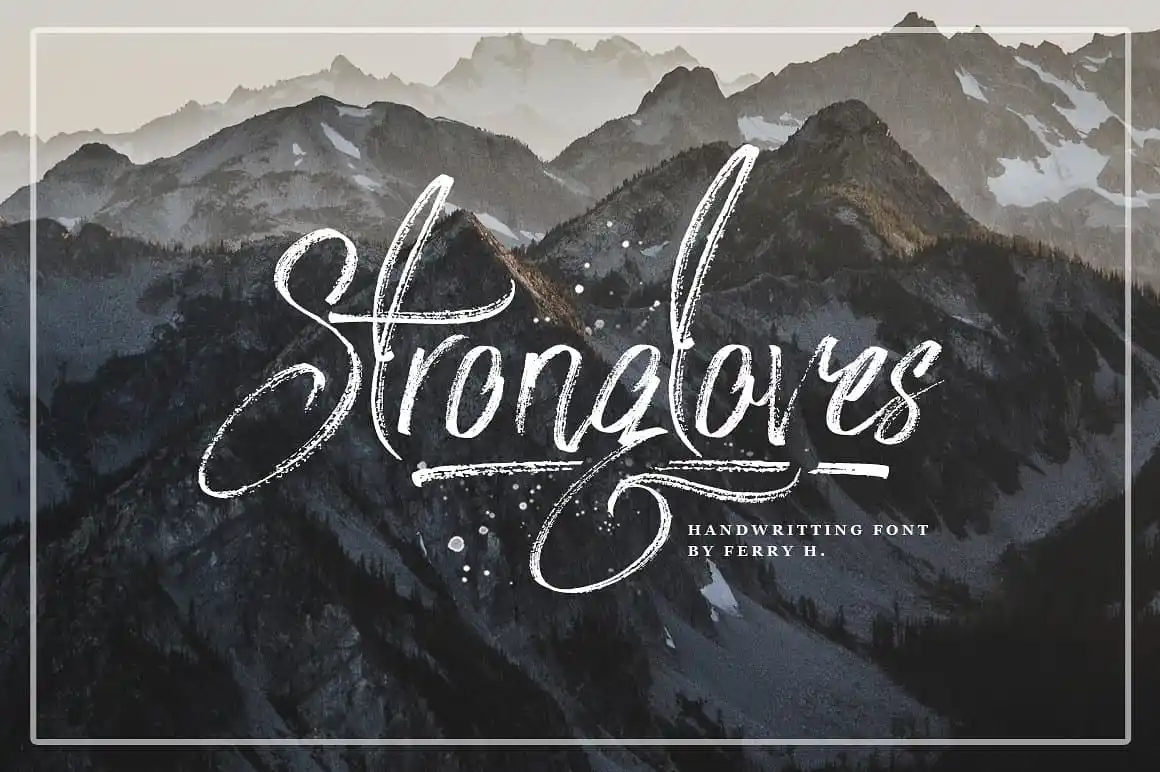
A Strongloves Handwriting Font é uma escolha perfeita para quem procura uma fonte de escrita manual para seu projeto futuro. Ela oferece ao seu público a garantia de um produto que os fará sentir satisfeitos e valorizados. Esta font foi projetada como uma fonte de escrita cursiva orgânica e expressiva, especialmente desenvolvida para versatilidade. Introduzimos Strongloves Handwriting Font – uma fonte de escrever com a textura da língua humana. Ela combina elementos do estilo de letra à mão com o estilo de esfumar de pincel, criando um ar natural e autêntico. Esta font é ideal para diversos usos, incluindo design gráfico, elementos de design, festas e eventos, camisetas, logotipos, selos, etiquetas e qualquer outro tipo de trabalho incrível. Strongloves Handwriting Font foi projetada por Ferry Hadriyan como uma fonte Dry Brush Script. Esta font é perfeita para quem busca um toque natural em seus trabalhos gráficos, seja para criar um design leve e elegante ou para dar um gás especial ao seu projeto de logotipo ou identidade visual. Com a Strongloves Handwriting Font, você pode expressar suas ideias de maneira única e criativa.